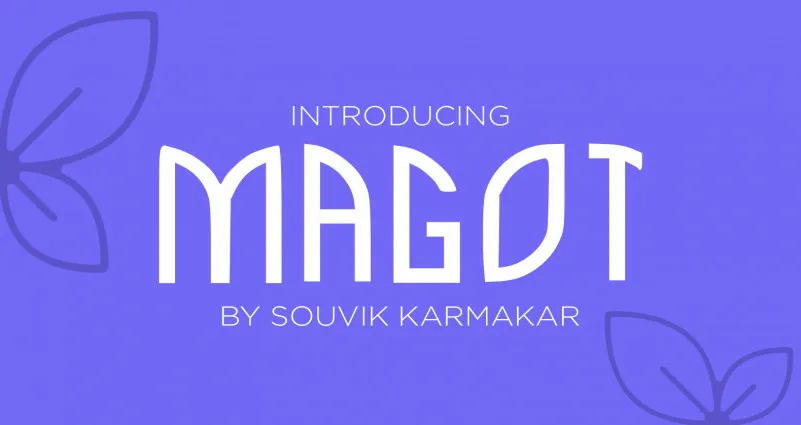
Magot Font – Download Grátis
A fonte ‘Magot Font’ é uma nova tipografia do tipo slab serif que se destaca pelo equilíbrio perfeito entre formas suaves e traços médios, criando um resultado elegante para projetos modernos e vintage. Ideal tanto para ambientes contemporâneos quanto para texturas mais tradicionais, a ‘Magot Font’ é uma escolha inteligente para designers em busca de um visual único e versátil. Sujeitada ao design do designer sênior souvikkarmakar, essa fonte oferece tanto um look fresco quanto um toque nostálgico, permitindo que os criadores adaptem seu estilo de acordo com suas necessidades específicas. Seja para aplicativos de web ou impressão, a ‘Magot Font’ é uma escolha confiável e versátil para aqueles buscando manter sua identidade visual contemporânea ao mesmo tempo em que incorpora um toque de sofisticação e originalidade.
Designer: souvikkarmakar